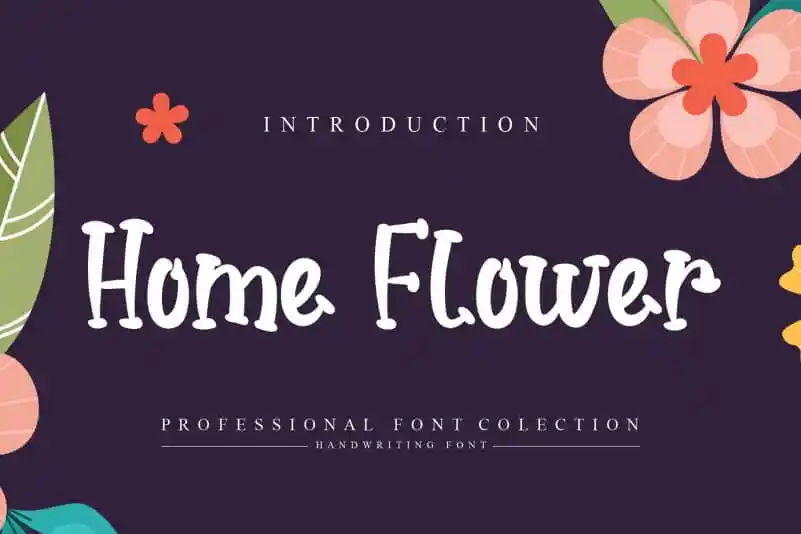
Home Flower Display Font – Download Grátis
A Home Flower Display Font é uma elegante serif que traz ao seu design um toque divertido e descompromissado. Suas linhas finas e delicadas complementam perfeitamente uma ideia de design casual, tornando-a perfeita para qualquer projeto que você possa ter em mente. Além disso, sua originalidade única e até mesmo um ar um pouco assustador fazem dela um item versátil em sua paleta de fontes, capaz de dar vida a qualquer arte visual. Ideal para quem procura uma combinação perfeita entre charme e frescor, Home Flower Display Font é a escolha certa para decorar seus designs com estilo. Com a designer experiente e criativa andikastudio, você pode garantir que sua impressão seja única e imprevisível.